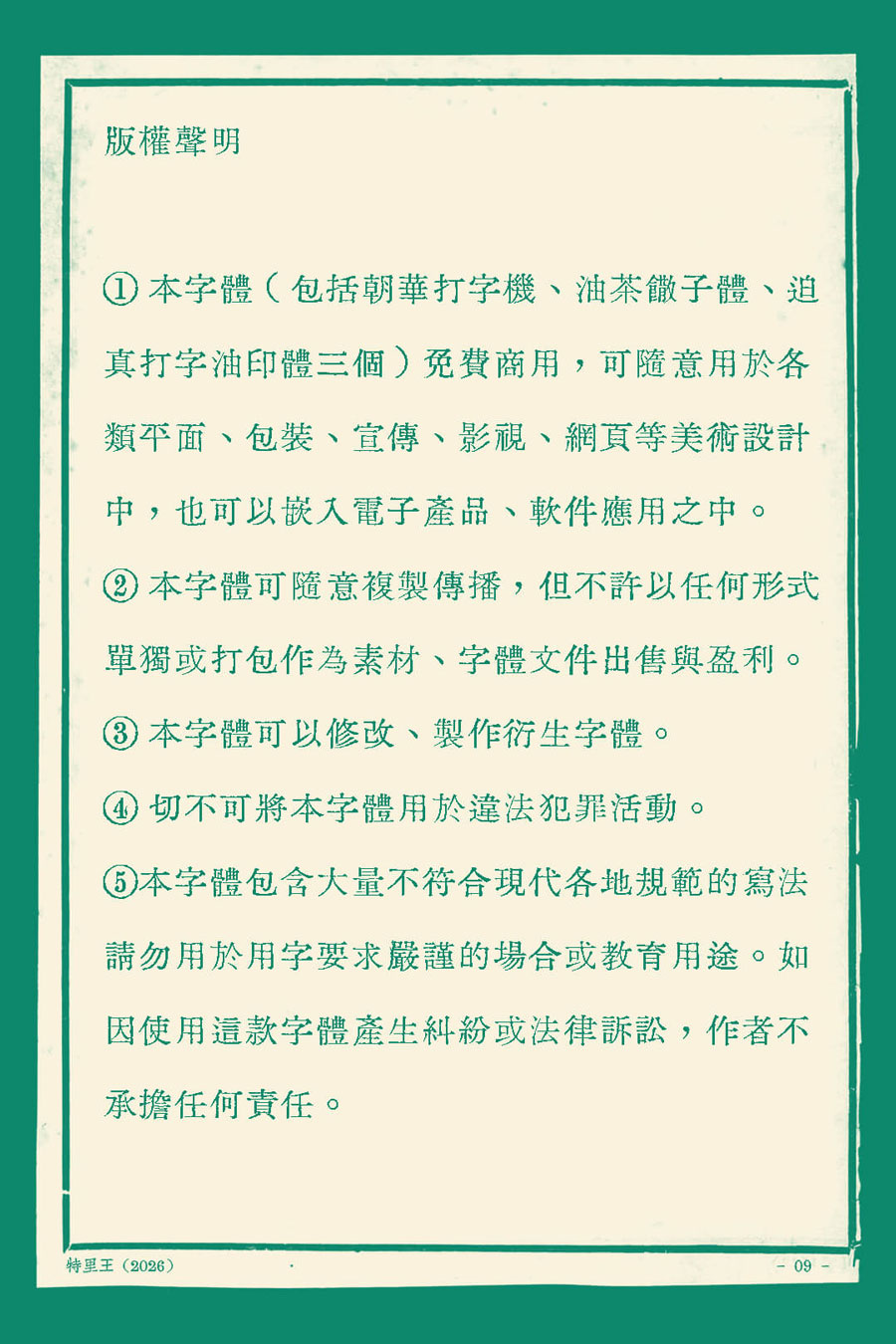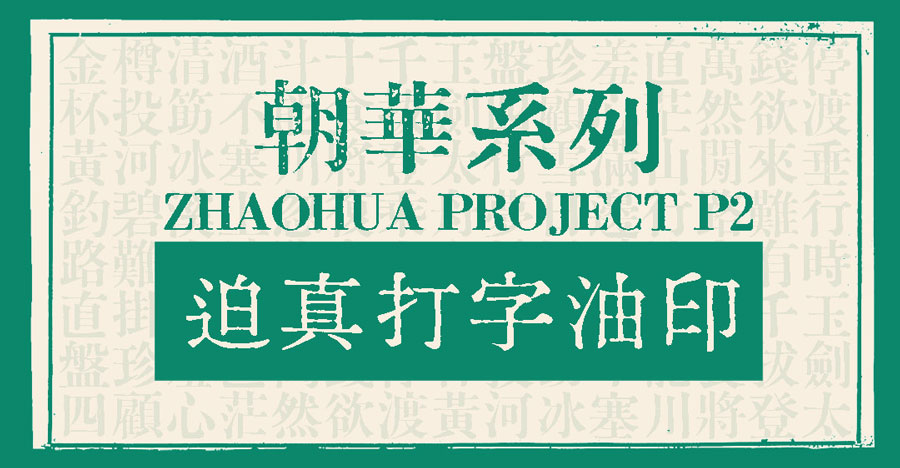
迫真打字油印体
迫真打字油印体 是由设计师特里王创作的一款免费可商用的复古中文字体,完美还原了打字机时代“缺字手写补填”的经典印刷状态。适合复古海报、怀旧风格视频字幕、古风类文创产品等多种场景用字需求。
迫真打字油印体(RealTypeWriter) 是由设计师特里王创作的一款免费可商用的复古中文字体。它是朝华打字机和油茶馓子体的混合版,常用字采用打字机明朝体,模拟打字机印刷质感;生僻字则采用油茶馓子手写体,模拟手写补字效果,真正还原了打字机时代“缺字手写补填”的经典印刷状态。
迫真打字油印体
迫真打字油印体完整收录 GB/T 2312 规范的全部 6763 个简体汉字,繁体覆盖五大码(Big5)13060 个常用字,收录汉字总量高达 35984 个。同时还整合了康熙部首、阿拉伯数字、大小写英文字母以及各类常用标点符号,能轻松应对复古海报、怀旧风格视频字幕、古风类文创产品等多种场景用字需求。